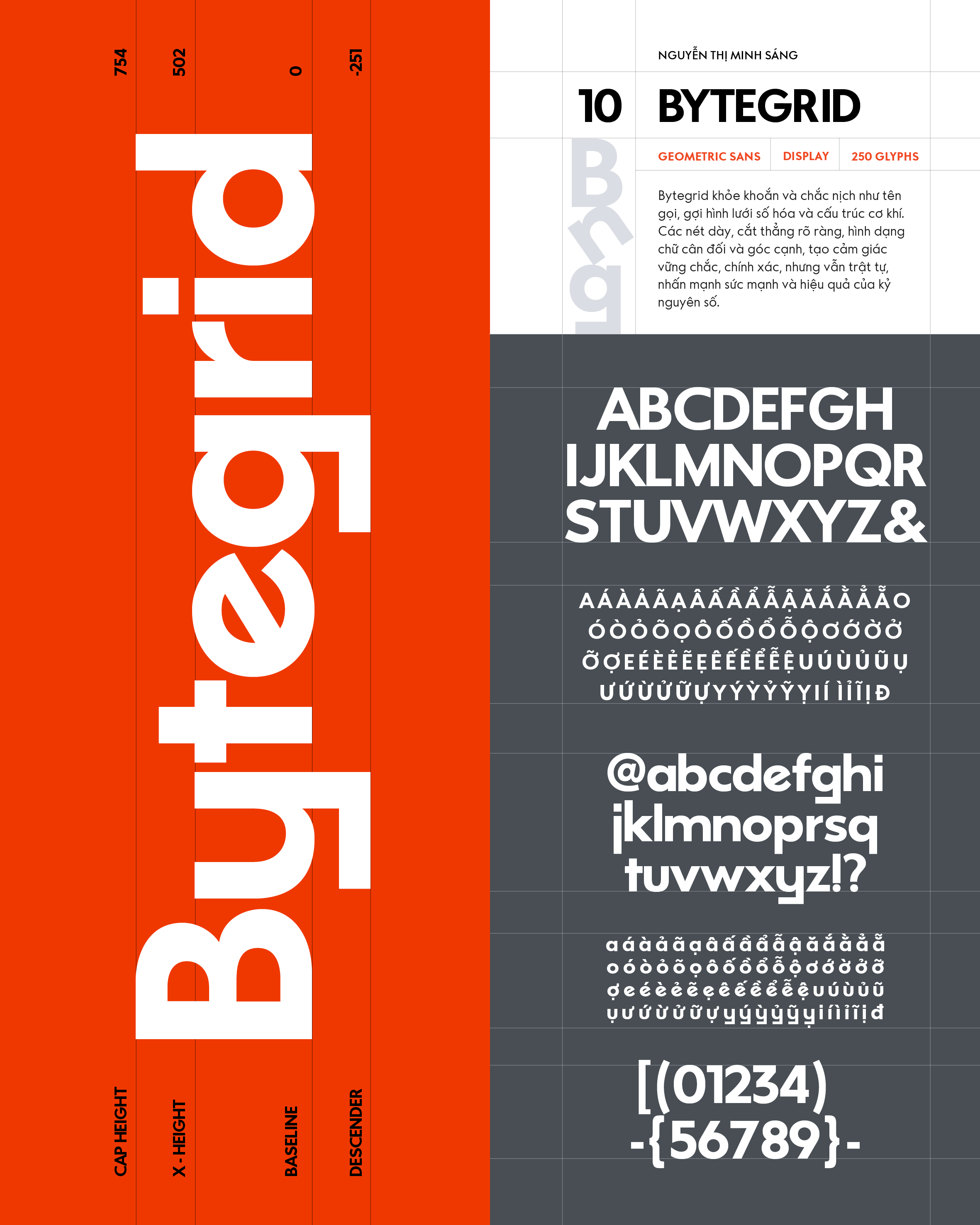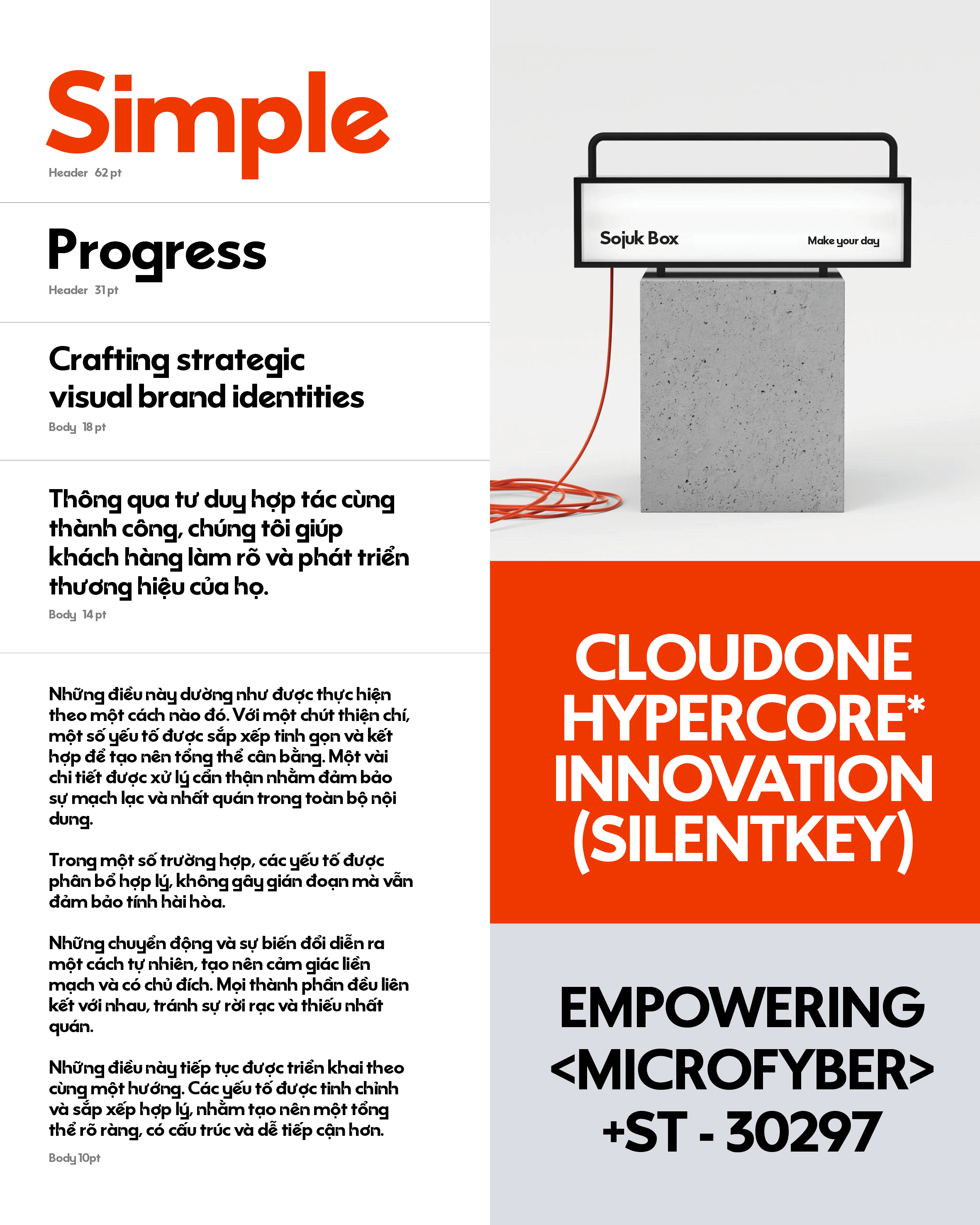
Bytegrid
Về Bytegrid: Bytegrid khỏe khoắn và chắc nịch như tên gọi, gợi hình lưới số hóa và cấu trúc cơ khí. Các nét dày, cắt thẳng rõ ràng, hình dạng chữ cân đối và góc cạnh, tạo cảm giác vững chắc, chính xác, nhưng vẫn trật tự, nhấn mạnh sức mạnh và hiệu quả của kỷ nguyên số.
Geometric Sans-serif
Display
Nguyễn Thị Minh Sáng
Bytegrid
Technology
Bytegrid
HYPERCORE INVENTION
Bytegrid
Thiện chí
Bytegrid
Tổng thể cân bằng
Bytegrid
ByteGrid is a technology company focused on providing secure data center, cloud, and managed IT infrastructure services, particularly for government agencies and enterprise clients.
Bytegrid
Founded in the United States, ByteGrid specializes in highly compliant environments that meet strict regulatory standards such as HIPAA and FISMA, making it a trusted provider for sensitive data storage and mission-critical operations. Its services include colocation, private cloud hosting, disaster recovery, and cybersecurity support, all designed to ensure reliability, scalability, and protection against threats. By combining physical data center infrastructure with cloud-based solutions, ByteGrid plays a key role in supporting digital transformation while prioritizing data security and operational continuity.